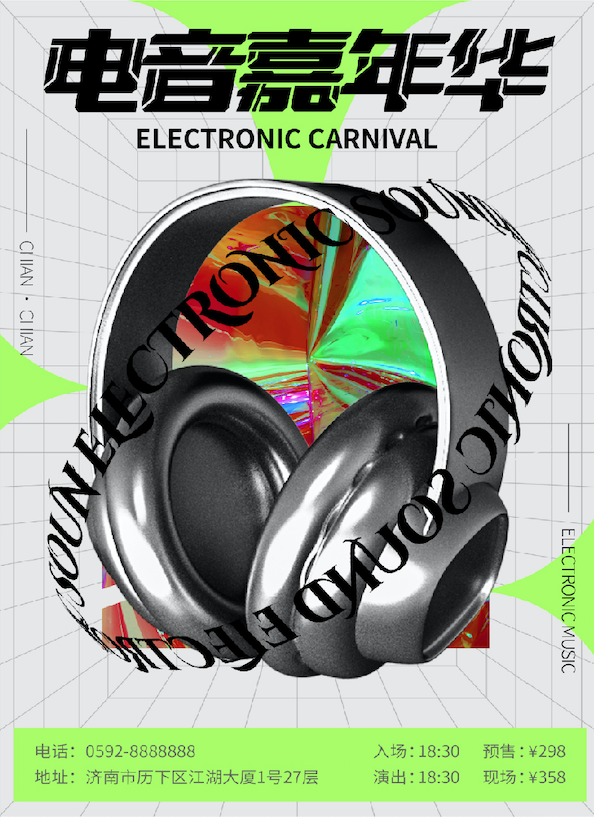
励字造梦,共创辉煌:四款代理字体推荐
在字体的世界里,每一个字都承载着独特的情感与故事。作为字体设计领域的领航者,携手代理品牌,不断推动字体行业的创新与发展。今天,我们为您精心推荐四款字体,它们不仅是技术与艺术的完美结合,更是激励梦想、共创辉煌的绝佳选择。
1.高手兵克战甲体
这款字体以其刚毅有力的线条,仿佛战士身披战甲,透露出不屈不挠的精神。它适用于军事、游戏等需要强烈视觉冲击力的场景,让您的作品瞬间脱颖而出,彰显力量与决心。
2.高手兵克侠客体
侠之大者,为国为民。这款字体融合了侠义与浪漫的元素,笔触间流露出一种超凡脱俗的气质。无论是书籍封面还是广告海报,它都能为您的作品增添一抹独特的侠骨柔情。
简约而不简单,这款大黑体以其粗犷而又不失精致的线条,展现出强烈的现代感与力量感。它适用于各种商业场合,如品牌标识、宣传海报等,能够迅速吸引眼球,提升品牌形象。
4.高手字斋东京体
一款充满异国情调的字体,融合了东京的都市气息与传统文化精髓。它的独特之处在于其流畅的线条与巧妙的布局,让人仿佛置身于繁华的东京街头。无论是旅游宣传还是时尚设计,它都能为您的作品增添一抹独特的风情。